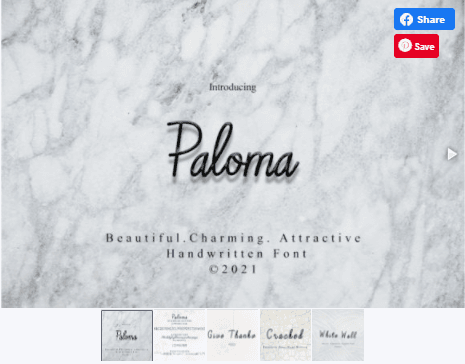
Paloma Font
Paloma - стильный и невероятно элегантный рукописный шрифт. Он потрясающе смотрится на свадебных приглашениях, цитатах, поздравительных открытках, логотипах, визитных карточках и любом другом дизайне, требующем рукописного ввода.